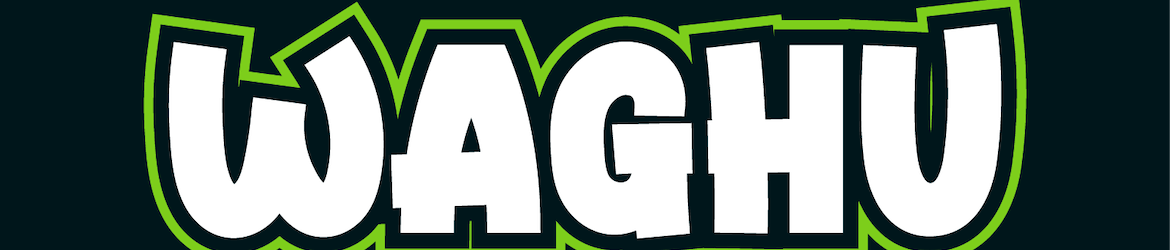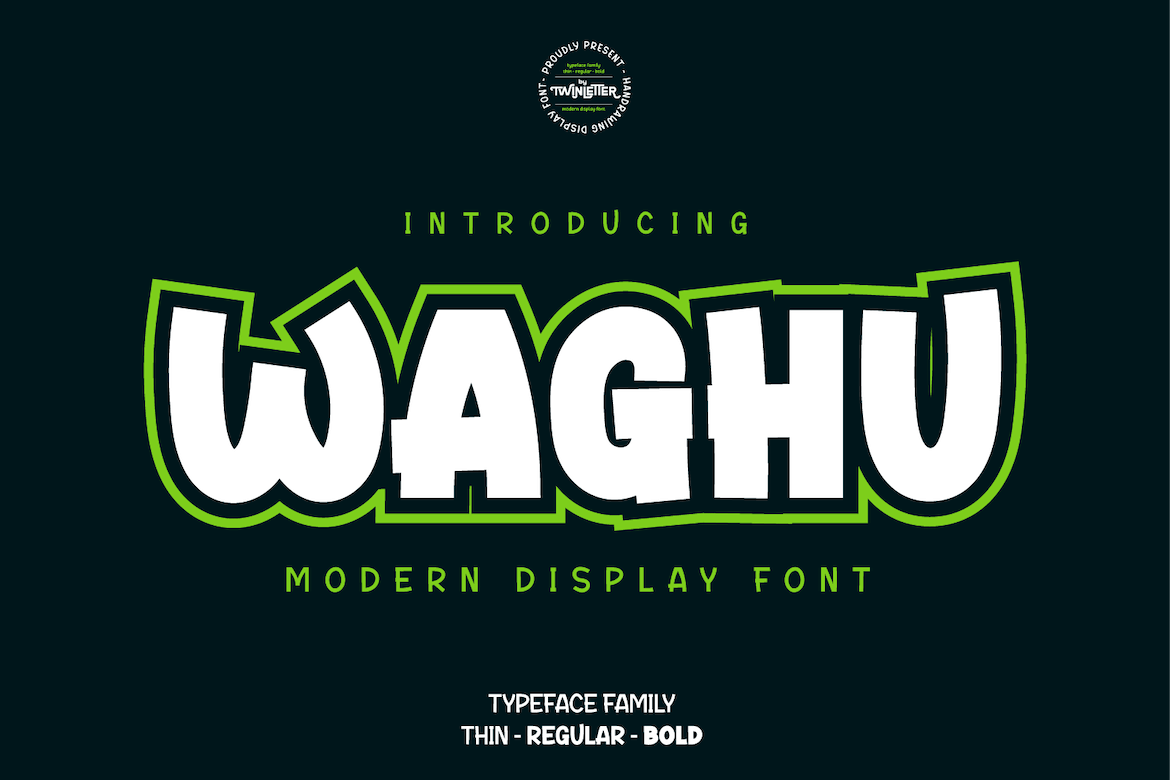
Waghu Font
Esta é uma fonte ‘display’ chamada Waghu Font, criada pelo designer twinletter. Obrigado a seus criadores por fornecerem uma descrição tão vívida e intrigante para essa fonte: “This is a cool, thick lettered and modern display font. A bit quirky and unique, this font will instantly make your designs stand out.” A Waghu Font é exatamente como o designer diz que é – um charme de letras grossas e moderno, com uma pitada de personalidade que faz ela ser única. Ela será perfeita para qualquer projeto visual que deseja destacar sua presença ou adicionar algo a mais à experiência do usuário. Seja em uma banner publicitário brilhante ou um layout web cheio de vida, a Waghu Font se tornará o elemento diferenciador no qual você está investindo.